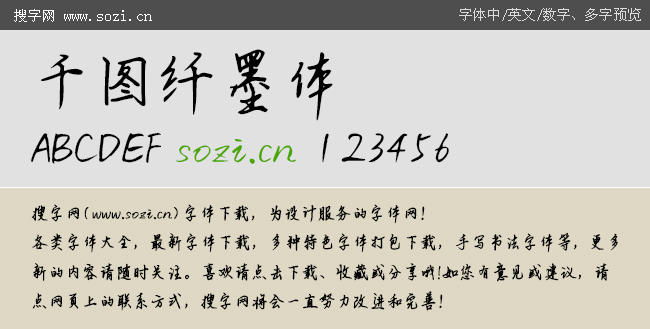
千圖纖墨體
搜字網(wǎng)給大家提供一款千圖纖墨體中文字體下載,千圖纖墨體是一款不錯(cuò)的手寫藝術(shù)字體,主要參考古代書法家書法,設(shè)計(jì)的一款手寫字體。字形纖細(xì)有力、運(yùn)筆自然、流暢,有如行云流水 。字間距緊湊,讓頁(yè)面看起來(lái)更飽滿、更豐富。適合應(yīng)用于藝術(shù)設(shè)計(jì)、平面宣傳設(shè)計(jì)、網(wǎng)頁(yè)設(shè)計(jì)、海報(bào)設(shè)計(jì)等應(yīng)用。